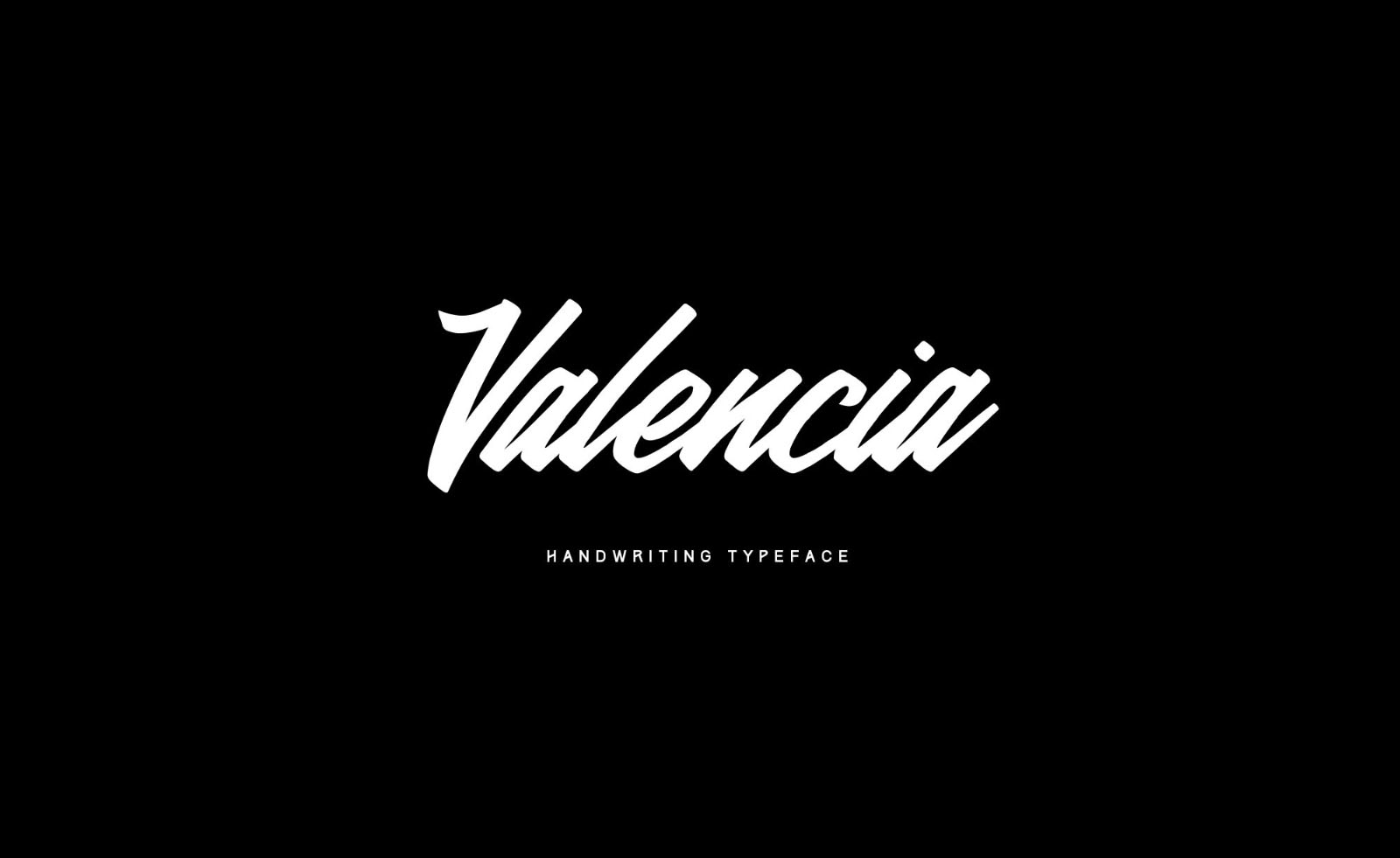
Valencia Calligraphic Font – Download Grátis
A Valencia Calligraphic Font é uma fonte chamada de tipo que traz o frescor de uma escrita manual. Ela se destaca no meio da fonte de tipo de caligrafia, conhecida por sua rica história e sua proximidade com a escrita humana. Esta fonte original é perfeita para criar logotipos, embalagens, cartazes e selos, além de inúmeros projetos de design gráfico e branding. Além disso, a Valencia oferece todas as letras maiúsculas, minúsculas, números e sinais em sua total desenvolvimento. Este recurso gráfico é uma maneira fascinante de tornar seus projetos ainda mais atraentes.